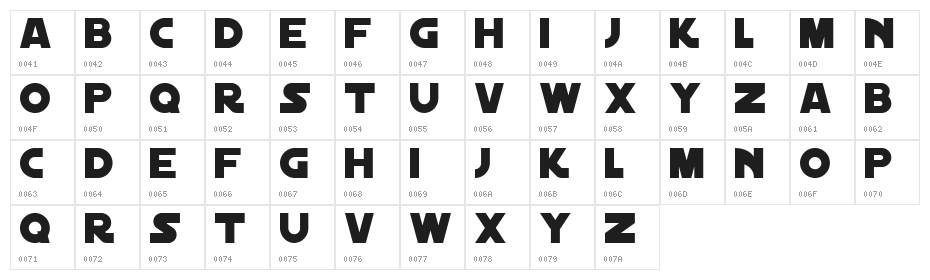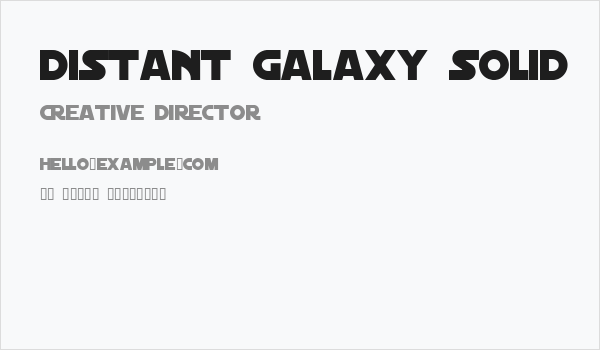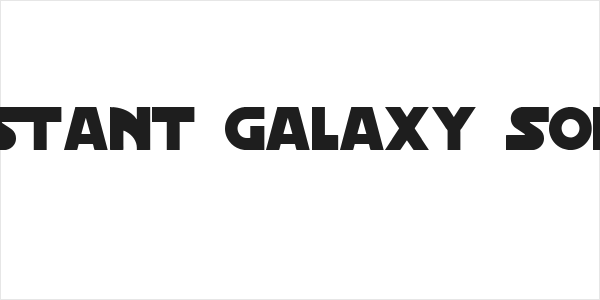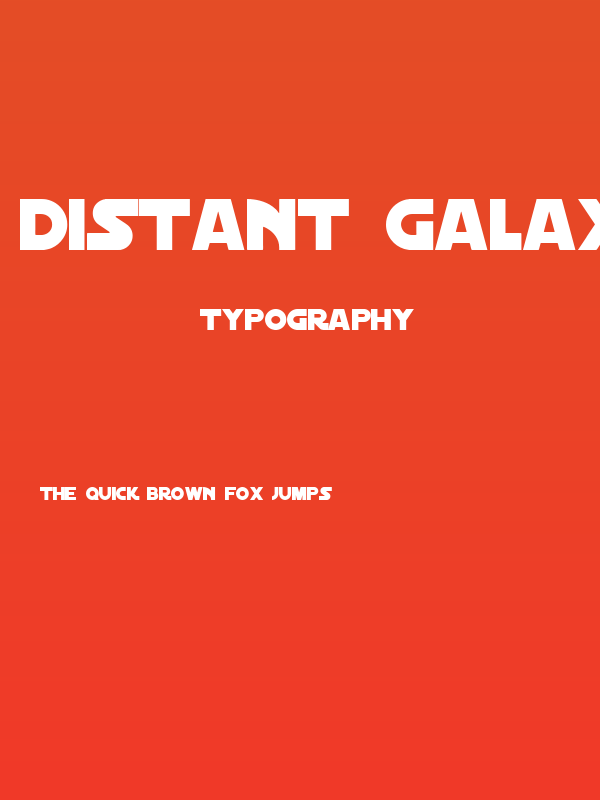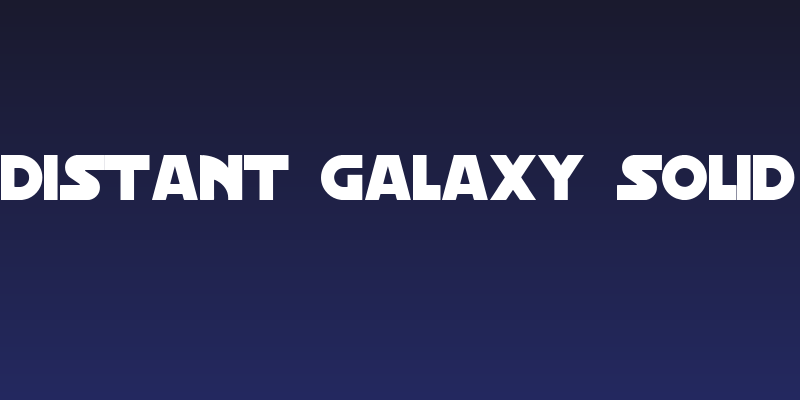
Distant Galaxy Solid Font
| Gesamtstil | Futuristic, Modern |
| Vorgeschlagene Projekte | Ideal for sci-fi themed designs, movie posters, video game titles, and branding that requires a modern, impactful look. |